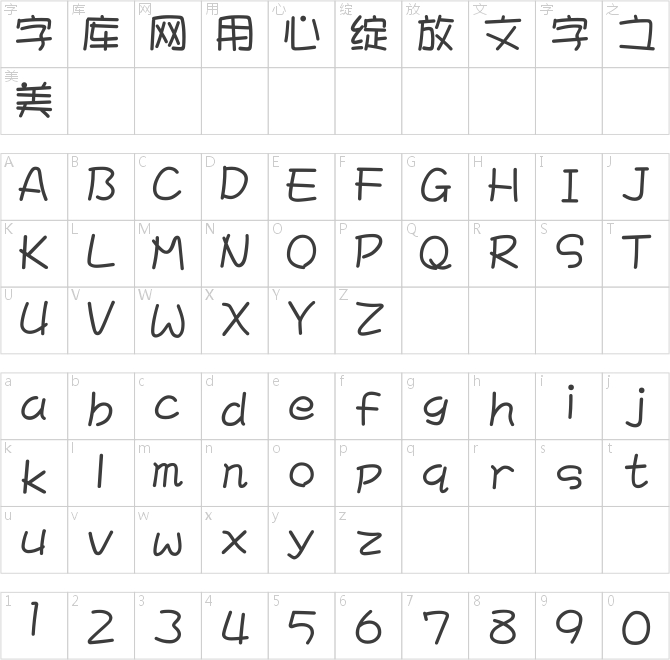
字體名稱: 文鼎POP-4
文鼎POP-4簡繁
文鼎POP-4的簡體和big5繁體合并成了文鼎POP-4簡繁,二次修訂時補全了原big5的漢字,該字體向上兼容新版win10。
文鼎POP-4簡繁字體字庫是一款讓人賞心悅目、百看不厭的中文字體,適合各類廣告和產品包裝設計應用,字體大小11.36MB,格式為ttf字體,上傳用戶是伊寧,作者/版權方為文鼎字庫